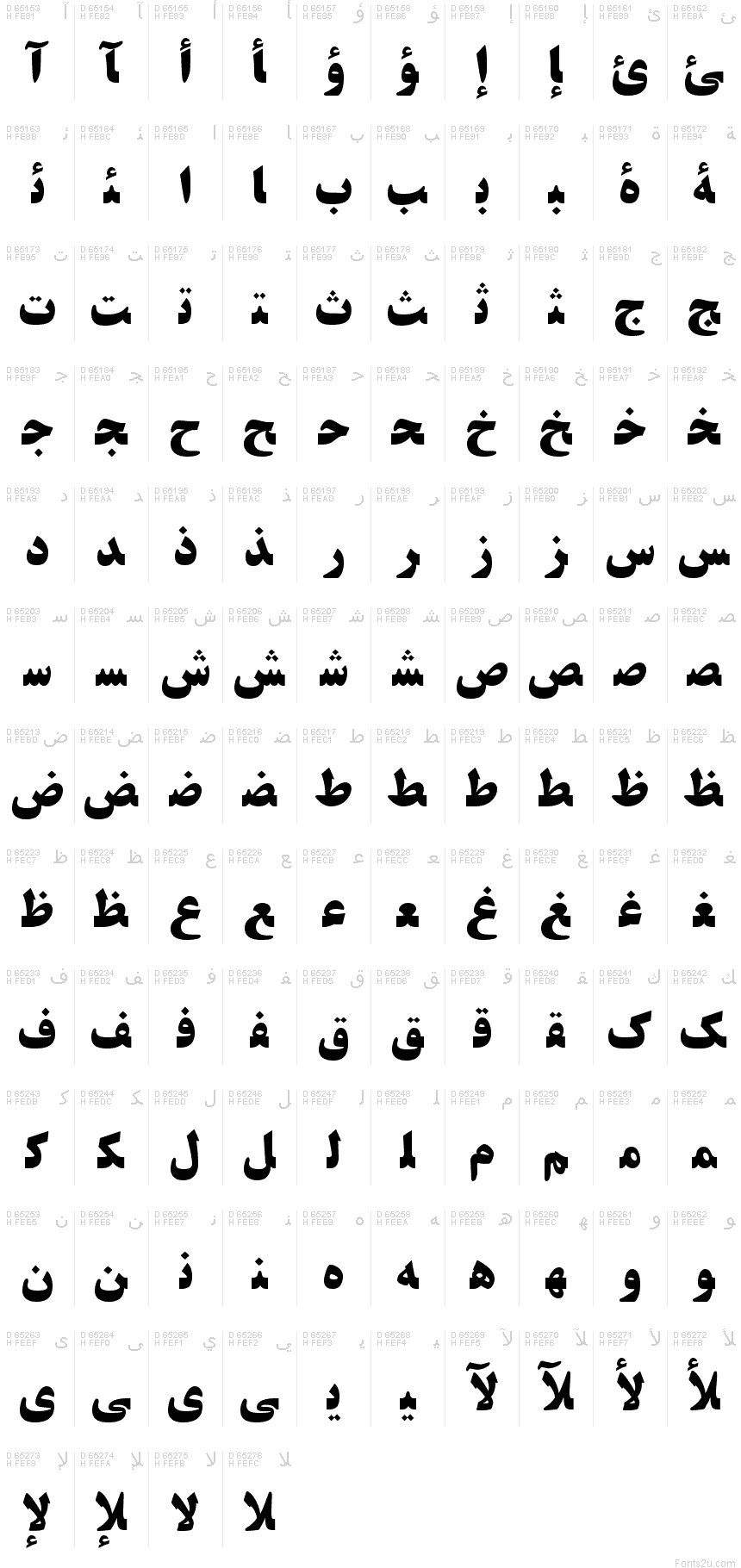
B Titr Bold de Borna Rayaneh é uma tipografia árabe gratuita do tipo display, com um peso caligráfico denso e um ritmo vertical firme. As letras transmitem uma sensação compacta e enfática, misturando traços curvos amplos com uniões nítidas que dão ao estilo uma presença de cartaz, distanciando-se de uma caligrafia manual fluida.
Isso torna-a uma escolha natural para embalagens, cabeçalhos, gráficos de eventos culturais, capas de livros e linhas de branding curtas onde é necessário um título árabe assertivo. Como é uma fonte gratuita, também funciona bem em cartões de título e sinalização, pois as formas pesadas e conectadas mantêm o texto visualmente unificado, mesmo em frases curtas e diretas.